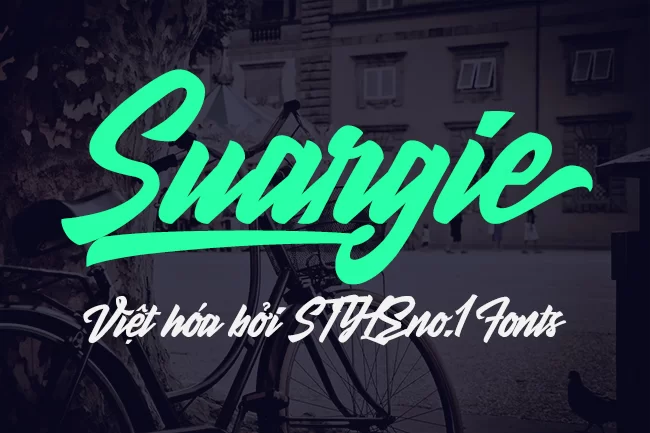
Mentari một kiểu chữ viết cọ, đậm và thanh lịch, với một vài ký tự thay thế trong mỗi chữ cái để bạn dễ dàng hoàn thành công việc của typographic như logo, poster, tiêu đề, T-shirt và các dự án sáng tạo khác.
Nhà thiết kế: Adil Budianto
Nhà phát hành: Adil Budianto
Năm phát hành: 2016
Việt hóa: STYLEno.1 Fonts
Kiểu: Regular
Phông chữ này hiện tại đã có version mới gọi là: Mentari